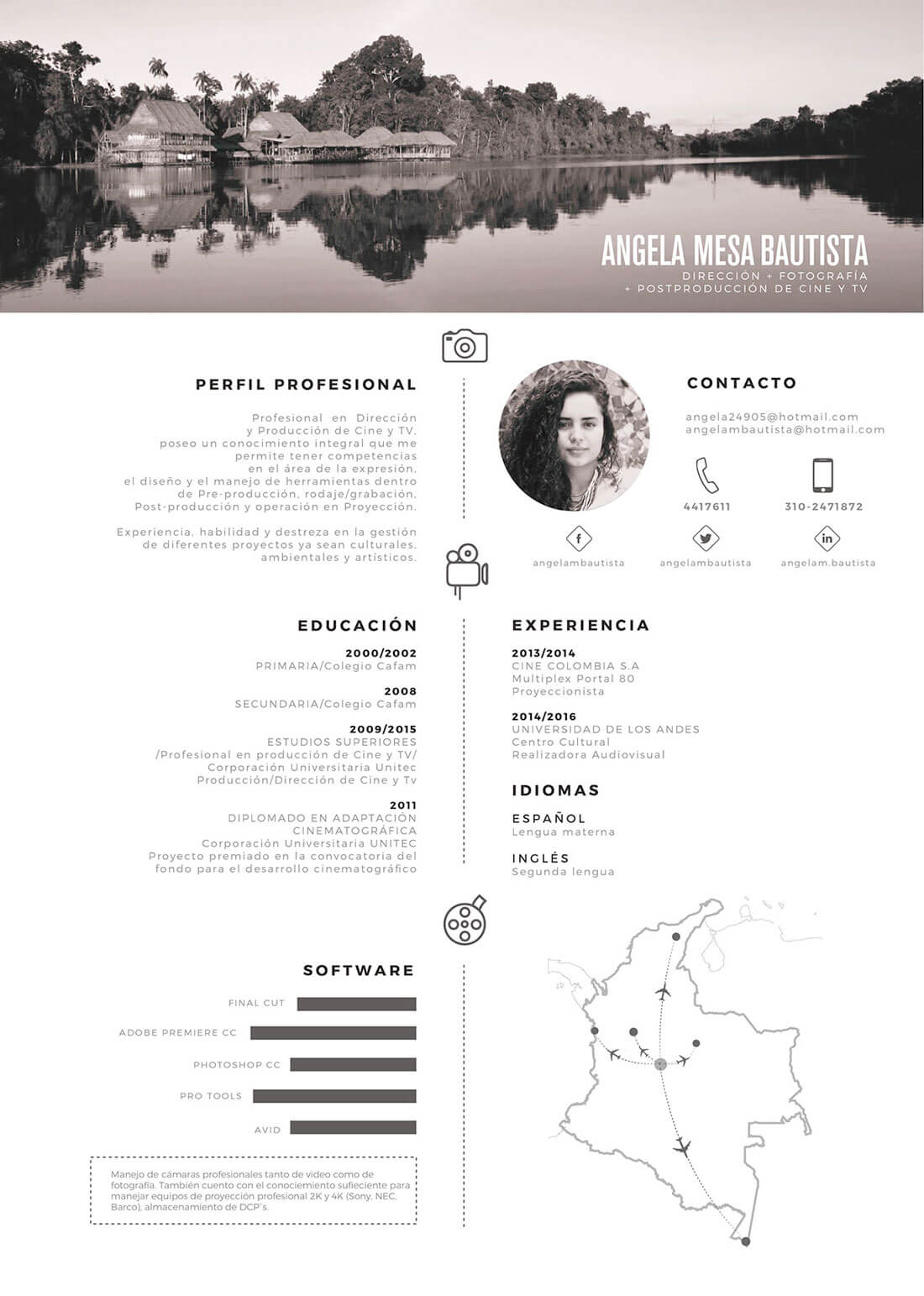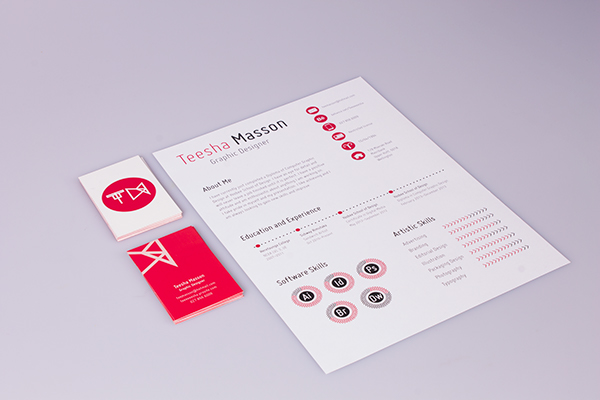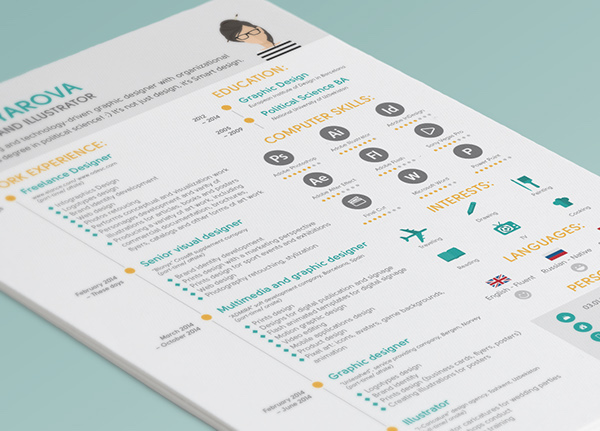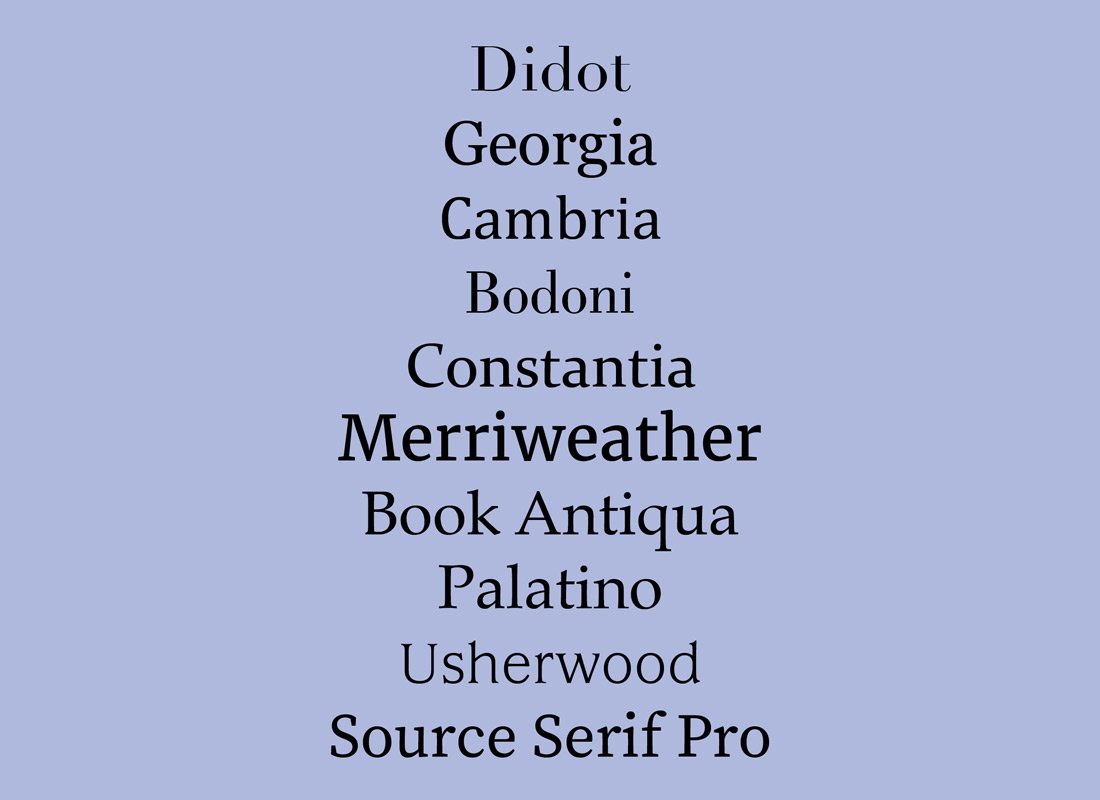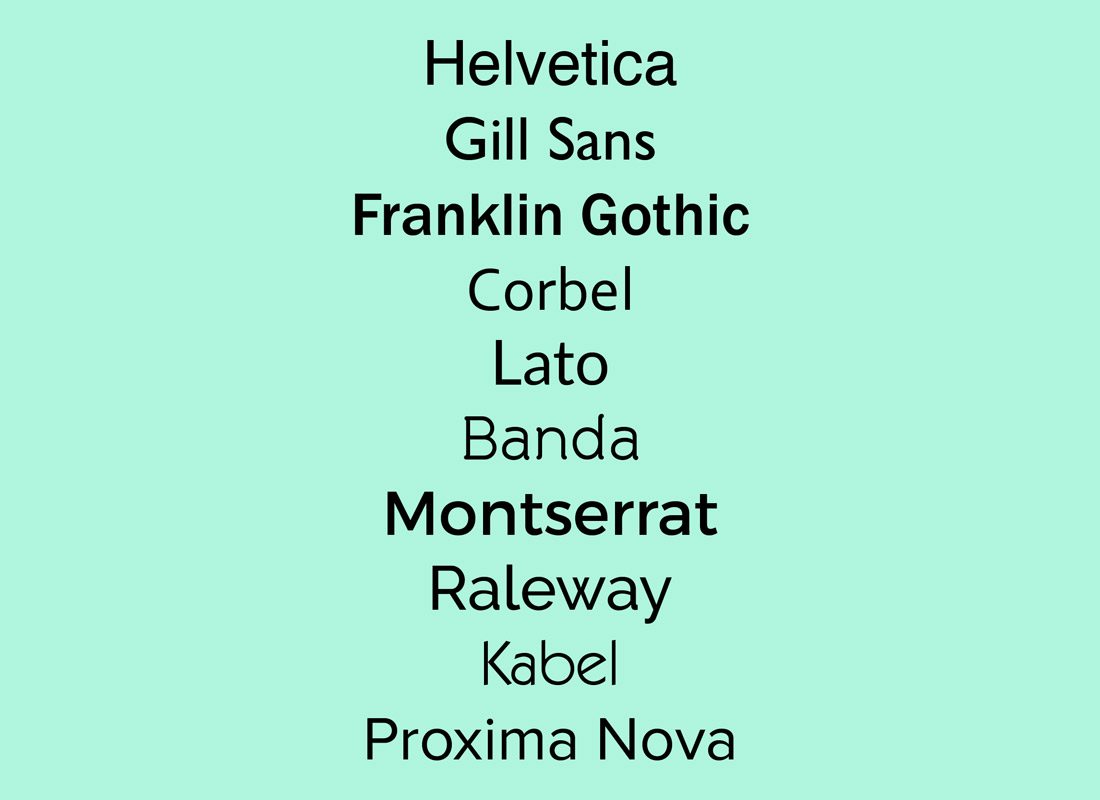
Quelle typographie choisir pour un CV ?
Un CV peut être considéré comme une affiche publicitaire visant à vous vendre. Donc, comme pour celle-ci, vous devez réfléchir à sa présentation. Et à sa typographie.
Hors de question de vous contenter de la première installée sur votre traitement de texte, sans aller plus loin.
Vous méritez mieux que cela.
Les polices Serif, celles qui ajoutent de petits traits à la fin de leurs lettres, comptent parmi les plus anciennes utilisées en typographie. Elles sont donc associées, dans l’esprit de ceux qui les regardent, à un petit côté classique.
Le message que vous passerez avec elles, dans votre page de publicité, sera : « regardez comme je suis fiable et raisonnable. Vous pourrez compter sur moi. »
Si c’est votre but, vous pourrez choisir parmi les polices de caractères suivantes :
Les polices sans Serif oublient volontairement les empattements qui caractérisent leurs aînées. Elles sont plus légères, plus modernes. Ce sont souvent elles que vous retrouverez sur les textes préparés pour des écrans, car elles sont aussi plus rapides à lire.
Elles apporteront à votre CV une apparence en accord avec l’air du temps. De vous, elles diront que vous êtes efficace, que vous ne perdez pas de temps et que vous vous adaptez à toutes les situations.
Voici quelques polices sans Serif qui seront parfaites pour des CV :
Sur une affiche, il arrive souvent d’associer deux typographies différentes. Une police Serif et une sans Serif, par exemple. La rencontre entre les deux apporte de l’énergie à la composition, et évite la monotonie. Elle permet aussi de hiérarchiser les niveaux de lecture.
Reprendre cette même technique sur votre CV aura les mêmes effets. L’astuce est de choisir des polices qui ont des points communs, mais suffisamment de différences pour ne pas être confondues.
Et, comme il s’agit d’un CV, vous oublierez les polices manuscrites ou trop fantaisistes, qui peuvent s’avérer difficiles à lire.
N’oubliez pas : la lisibilité reste le point le plus important pour un CV. Pour cela, vous opterez pour une taille de police comprise entre 11 et 13. Les titres pourront être jusqu’à 5 points plus grands que le reste du texte.
Il reste possible de présenter certains détails en taille 10, mais c’est une option dont vous userez avec modération. Vous n’avez pas envie que les recruteurs s’usent les yeux à tenter de vous lire.
Quand vous créez votre CV, pensez aux éléments sur lesquels vous voulez attirer l’attention en premier.
C’est eux que vous mettrez en avant avec des polices plus grandes, plus larges, ou juste différentes. S’ils semblent trop condensés, ou difficilement lisibles, changez de police. C’est aussi simple que cela.